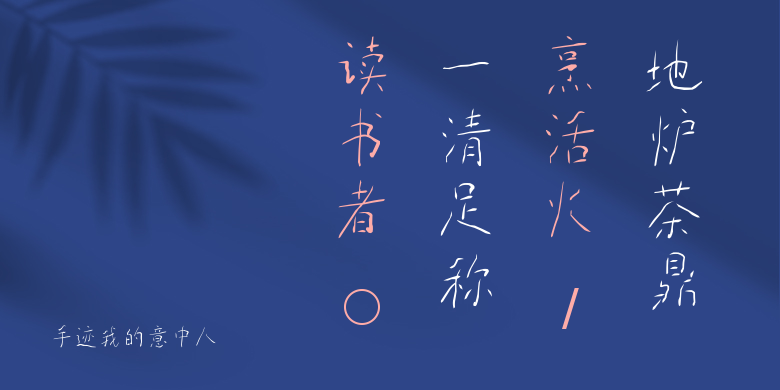
手迹我的意中人
手迹我的意中人,这款字体结构工整、笔画清晰,兼顾美观与易读性,适用于标题、正文、海报、包装、LOGO 等多种场景。字形优雅稳定,风格百搭耐看,适配日常排版与创意设计,让文字呈现更舒适、更具质感。手迹我的意中人一笔一画,皆是细节,以均衡的比例、流畅的线条打造舒适视觉体验,字形端正大气,风格简约现代。无论是商业设计、品牌宣传还是日常排版,都能轻松驾驭,让文字更有格调与力量。手迹我的意中人字体下载。